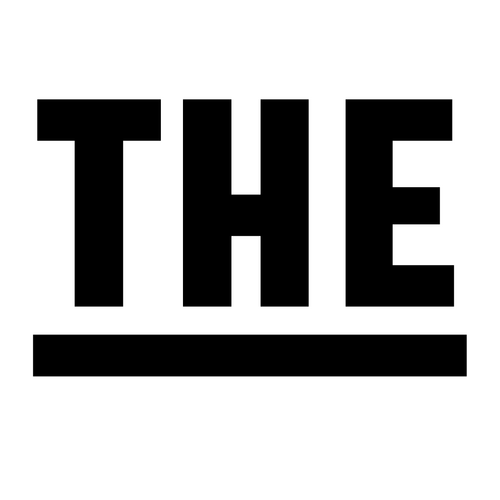
Die Avory von Slava Jevčinová wurde von den Lettering-Arbeiten des Tschechischen Designers Jaroslav Benda inspiriert. Auffällige Eigenheiten der schmalen Schrift sind die weit heruntergezogenen Bögen am C/c sowie die breiten Querverbindungen V/v, W/w, X/x und Y/y.
Die ebenfalls von Lettering-Anwendungen inspirierten, auf der Grundlinie unterstrichenen Versalien gehören ebenfalls zum Zeichenumfang.
Die Schrift besteht aus neun Strichstärken mit Kursiven und alle Schnitte sind in erweiterter lateinischer, kyrillischer sowie griechischer Belegung verfügbar.